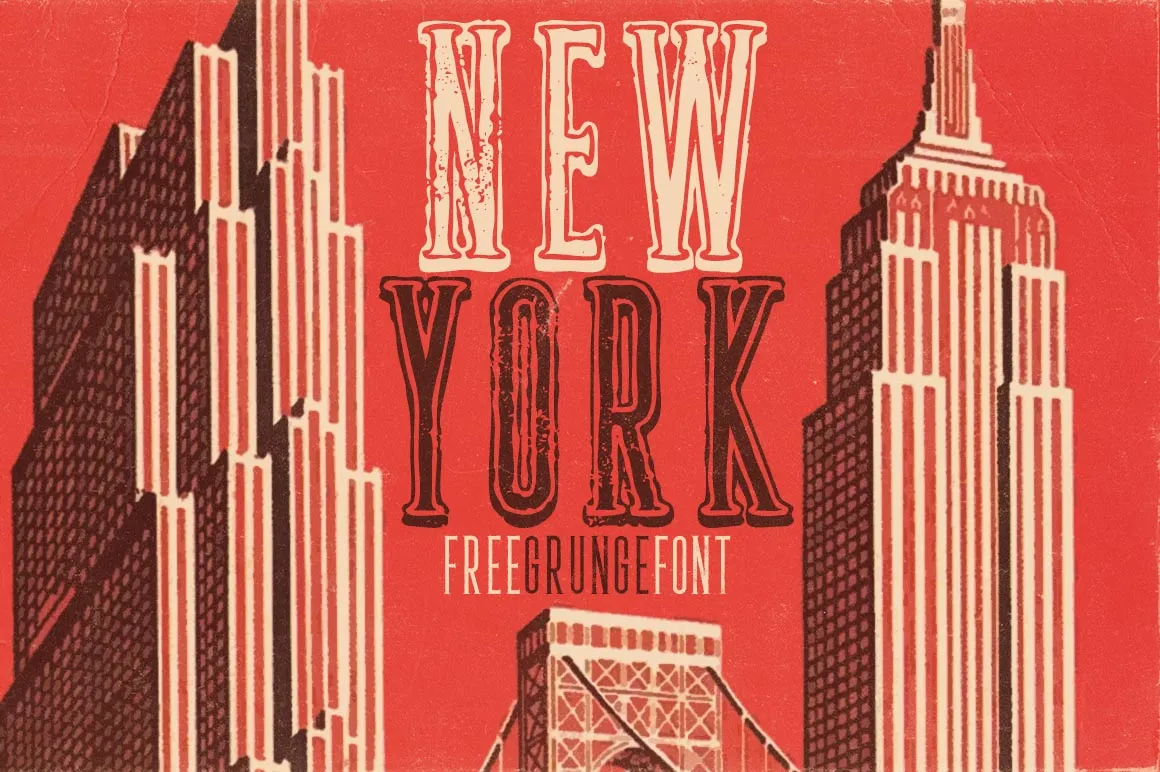
Nova Iorque é uma fonte serif criativa que faz alusão à década de 1980 ou até mesmo ao início do século XXI, com seus traços marcantes e estilo alternativo. Inspirada na estética da Nova York dos anos 70, esta fonte vintage oferece um toque retro e moderno perfeito para designers que buscam dar seu projeto uma identidade única. É especialmente adequada para títulos e headlines, onde as serifas dão um ar de elegância à qualquer design. Esta font foi criada por Hamilton, destacando-se pela sua personalidade vibrante e desafiadora, sem perder o caráter profissional que a torna tão versátil. Para designers que valorizam estilos fora da caixa, Nova Iorque é uma escolha ideal para projetos inovadores e memoráveis. Descarregue esta fonte agora e deixe seus trabalhos destacarem-se no mercado de design.